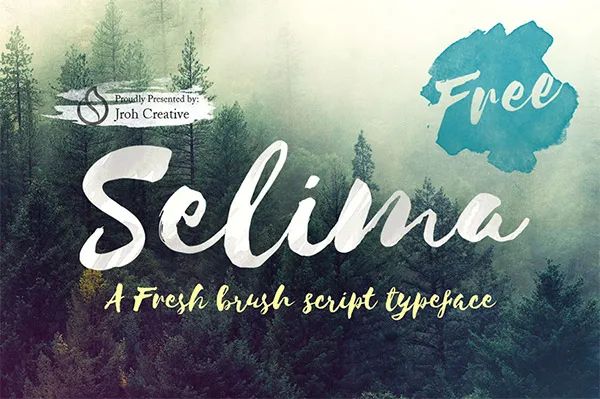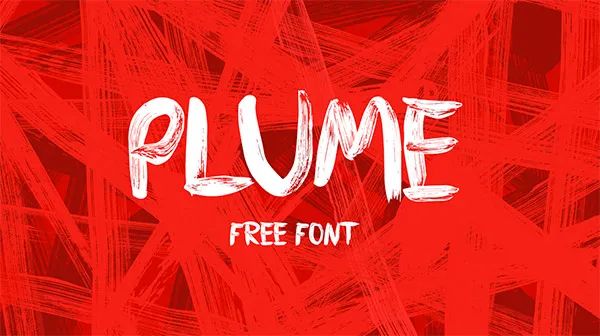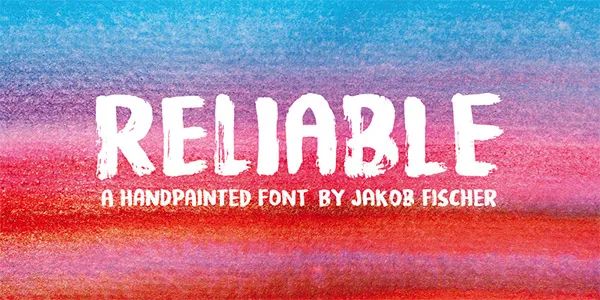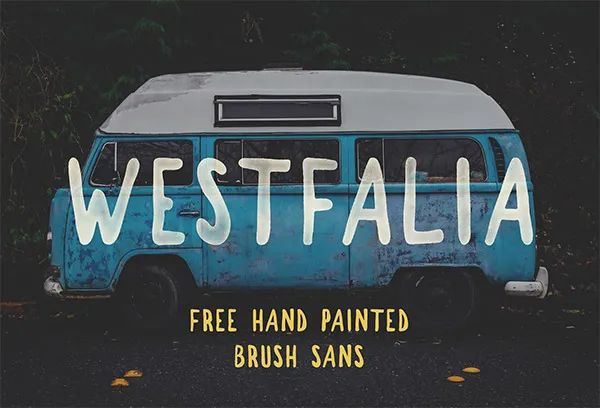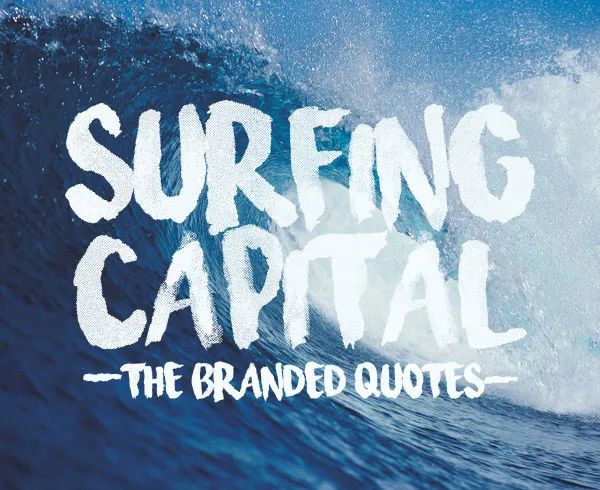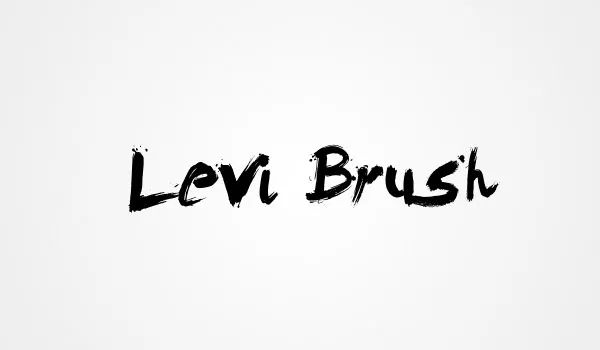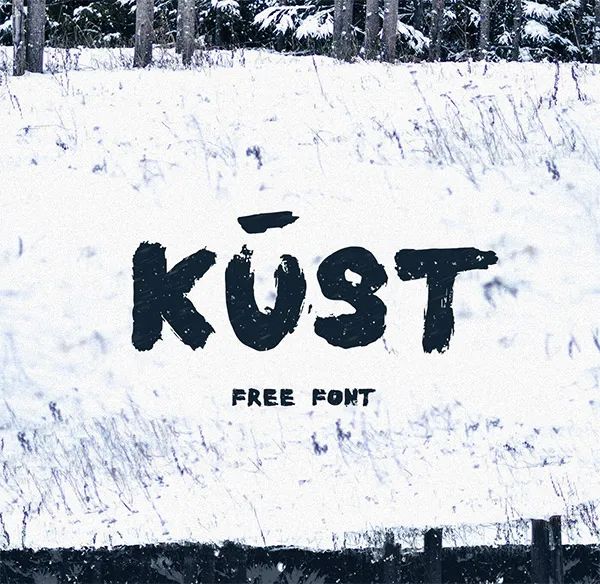
7款供设计师使用的水彩字体
有一些美丽的东西也会存在着不完美。有时,设计师会利用这些不完美的细节来设计出令人印象深刻的设计。其中一个很好的例子是水彩效果。它通常显示出不均匀的颜色深浅和杂散的笔触,使其在美学上更加华丽。
如果你想在设计中添加具有水彩效果的文字,那么这些字体样式可以帮助到大家获得出色的效果。今天我精心挑选了一些,和大家一起分享。
01Selima Script
Selima Script 是毛笔字体,具有漂亮的不规则形状和基线。它适用于令人眼花缭乱的消息和字体叠加。
02Plume
这种创意和潦草风格的字体可用于个人设计项目。Plume 带有所有字母数字和特殊符号,包括拉丁字符。
03Reliable
Reliable 是用有点干的毛笔画出来的,然后小心翼翼地做成字体。它不同于其他画笔字体,因为它每个字母有8个不同版本的!!!当然,Reliable也有很多变音符号。因此,如果你需要一个很酷的画笔字体,不妨试试它。
04Westfalia
Westfalia是一款来自 Pixel Surplus 的手绘笔刷。这种字体以其凌乱的边缘和不同的线条粗细提供了真实的手绘感觉。非常适合与户外和探索相关的任何设计工作。
05Surfing Capital
Surfing Capital 也是一种具有水彩效果的全大写字体,个人可免费使用。字体的灵感来自于对乘坐海浪的极度热情!它的自然和不完美的形状与它自己的纹理效果很好。可满足你的设计和照片对复古而又前卫的需求。
06Levi Brush
Levi 有漂亮的画笔细节,在水彩效果上看起来很棒。来自  Levi Szekeres 的作品。
07KUST -  Brush Font
新的 Kust 字体是一款手写字体,由时装设计师和画家 Ieva Mezule 设计。每个字母都有独特的结构,外观扭曲。这些字母是用纯黑色墨水用粗毛笔在硬纸上绘制的。